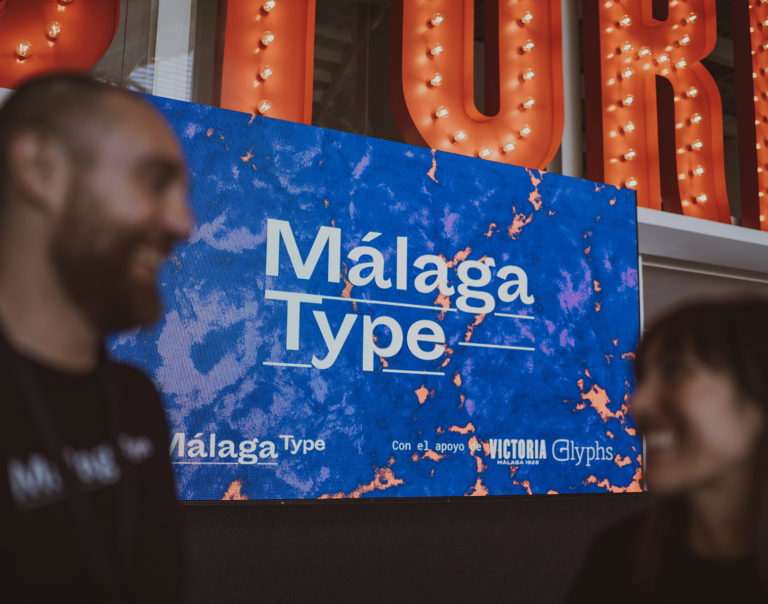
Amantes. Muchísimos amantes de las letras. En total, unos 180. Todos ellos reunidos bajo un mismo techo: el de la Fábrica de Cervezas Victoria, un espacio que refleja la tradición de su mítica cerveza malagueña en un entorno moderno y con un programa que apuesta por la cultura en la ciudad.
En Rayitas Azules hemos tenido la oportunidad de celebrar allí la primera edición de Málaga Type, que aún nos tiene recuperando el aliento, pero también muy felices por el resultado que ha generado. Ni que decir tiene que la noche anterior prácticamente no pegamos ojo, pero valió la pena. ¡Digo que si valió la pena!
Arrancamos la jornada del pasado viernes 25 de octubre a las 10 de la mañana con el workshop de Glyphs, impartido por el diseñador de tipos y traductor Rainer Erich Scheichelbauer, quien se encarga de crear tutoriales y manuales para este software de edición de fuentes.
Los 15 asistentes al workshop pasaron unas horas aprendiendo algunos de los entresijos de este software y las posibilidades que ofrece en cuanto al diseño y la animación en el campo tipográfico. Además, nuestra compañera Ana Moliz estuvo resolviendo algunas dudas y revisando los proyectos de los alumnos.
Tras este comienzo intenso y productivo, hicimos parada en Horno Beach Club en La Carihuela (recomendadísimo) y, tras tostarnos un rato al sol, disfrutamos del almuerzo junto a algunos amigos y compañeros del sector como Pascal Zoghbi, de 29Letters, Pedro González, de PeGGO Fonts, o Victor Palau, de Gràffica, entre otros. Cabe mencionar que muchos asistentes no quisieron perderse este día tan importante y viajaron desde lugares como Oviedo, Barcelona, Madrid, Valencia, Chile, Bulgaria, Bélgica o Inglaterra. Una auténtica pasada lo que mueve el interés por la tipografía y el diseño editorial.
Pero esto solo fue un aperitivo comparado con lo que nos esperaba a partir de las 18h: el plato fuerte con nuestros ponentes. Tras abrir las puertas y recibir a los asistentes con un regalo por nuestra parte, Salva Cerdá y Ana Moliz que, como ya sabréis, son los cofundadores de este blog, presentaron el evento y dieron paso a Noe Blanco, no sin antes agradecer a todos los patrocinadores y colaboradores el apoyo que han demostrado.
Noe Blanco es diseñadora de tipografías y font engineer. Natural de Barcelona, ha estudiado tanto allí como en La Haya. Y, con toda su experiencia, sobre todo trabajando para Underware y, actualmente, para Klim Type Foundry, así como colaborando con Tobias Frere-Jones, Blackletra o FosterType, vino a Málaga Type 2019 para contarnos a todos cómo fue profesionalizando su carrera como diseñadora de tipografías. Pero, ojo, que también nos contó otros aspectos de su vida como, por ejemplo, que cantaba en una banda de punk.
Pudimos ver muchos de sus trabajos y nos fue explicando algunos detalles tanto de estos como de los clientes que los encargaron. Algunos de ellos fueron Financial Times o la mismísima National Geographic. ¡Poca broma! En cualquier caso, si no pudiste asistir, aquí puedes leer la entrevista que hicimos a Noe Blanco y conocer un poco más sobre ella.
Tras su ponencia, subieron al escenario Roberto Espartero y Juan Martín, los creadores del proyecto Alioli es Ajonesa. Ambos, diseñadores de profesión, se dedican a documentar la imagen y tipografía de los rótulos de Málaga, algunos incluso ya desaparecidos. Lo cierto es que nos sorprendieron con una ponencia en la cual reímos y nos emocionamos a partes iguales.
Nos contaron anécdotas como la del intento de conservación del rótulo del Cine Victoria y que, desde hace poco, están colaborando con otros ilustradores como Laura Wächter o Fer Ávila, que han dado una vuelta de tuerca a míticos negocios como el Restaurante Chinitas o el desaparecido Onda Pasadena.
Por cierto, los chicos de Alioli es Ajonesa tuvieron el detalle de regalar a cada asistente un imán tipográfico que representa una letra de algunos de los rótulos que han documentado. Vamos, que se hicieron querer de lo lindo y no es para menos.
A continuación, y para cerrar el ciclo de ponencias de esta primera edición de Málaga Type, subió al escenario Pedro Arilla, autor del blog Don Serifa, ahora reconvertido en una magnífica newsletter y podcast, de la que no podemos ser más fans.
Pedro es diseñador de tipos y, junto a Damiá Rotger, artífice del curso intensivo de tipografía Glíglifo. Además de contarnos su experiencia estudiando en Reading, nos mostró sus primeras tipografías y otras tantas que ha diseñado en Fontsmith, fundición en la que trabaja actualmente.
Nos habló de tipos como FS Neruda y otros trabajos para proyectos como el del primer logotipo responsive, de tipografía variable, para Amsteldok, que te recomendamos que conozcas para que veas cómo funciona a través de factores como el tiempo y las interacciones con el entorno. Por cierto, a Pedro también tuvimos el placer de hacerle una entrevista para nuestro blog.
Después de las tres magníficas ponencias, llegó el momento del Tipo Quizz. Tras la competición en tiempo real y algunas preguntas y respuestas que causaron bastante revuelo entre los cientos de participantes, entregamos los premios a los ganadores, que se llevaron regalos como el último número de la revista Gràffica, que trajo el mismísimo Victor Palau, libros cortesía de la editorial Campgràfic, una de las colaboradoras del evento, y especímenes de Typerepublic. Casi nada, vamos.